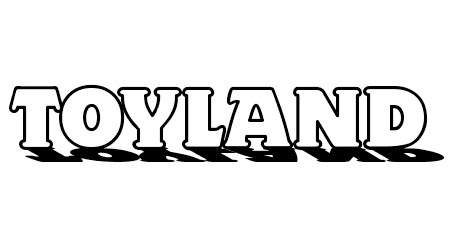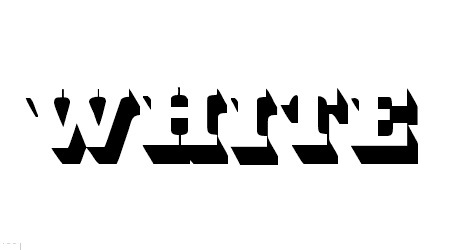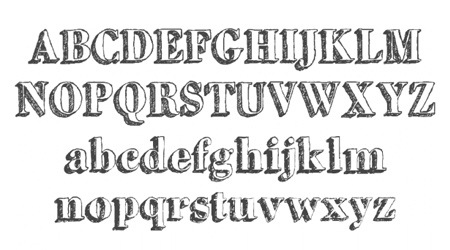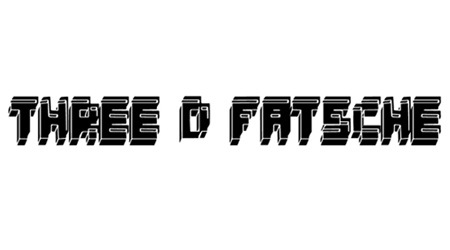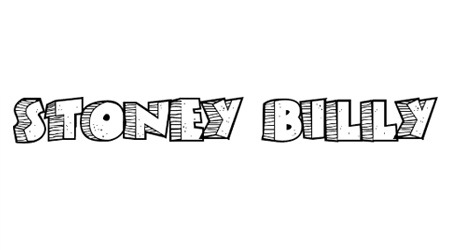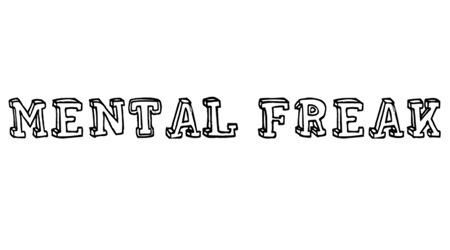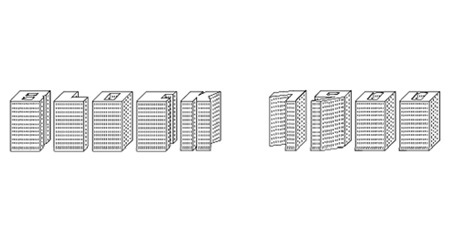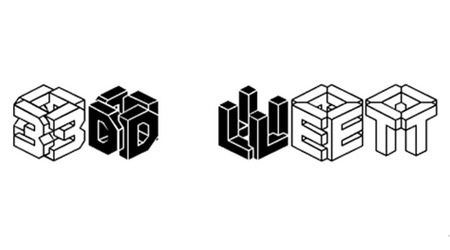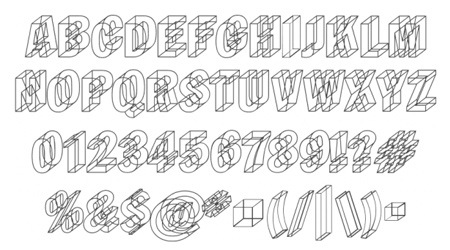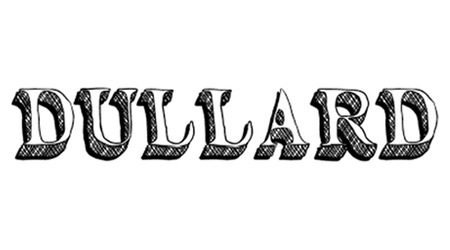
25 бесплатных 3D шрифтов
3d-шрифты В этой подборке, вам будут продемонстрированы шрифты хорошо знакомые каждому. Это шрифты в стиле 3D. Такие шрифты очень часто используют а дизайне постеров. Они способны добавить глубины изображению и придать стильный эффект дизайну в целом.
Тут вы найдете 25 различных 3D шрифтов. Все их вы сможете загрузить абсолютно бесплатно. Загружайте 3D шрифты и делайте свои работы более привлекательными!
Шрифт DULLARD
Шрифт
Наведенный шрифт esquisito
Наведенный шрифт
Кубический шрифт cubus
Кубический шрифт
Забавный шрифт shutdown!
Забавный шрифт
Округлый шрифт Chocolate Drops
Округлый шрифт
Шрифт с пикселями Blockstepped
Шрифт с пикселями
Размытый шрифт Snarky’s Machine
Размытый шрифт
Шрифт в восточном стиле Hawkeye
Шрифт в восточном стиле
Объемный шрифт Xtrusion
Объемный шрифт
Шрифт с тенью TOYLAND
Шрифт с тенью
Крупный шрифт White
Крупный шрифт
Шрифт в стиле гранж GrutchShaded
Шрифт в стиле гранж
Стильный шрифт 3d-fatsche
Стильный шрифт
Иллюстрированный шрифт Stoney Billy
Иллюстрированный шрифт
Тонкий шрифт Mental Freak
Тонкий шрифт
Шрифт в виде блоков block 1900
Шрифт в виде блоков
Затертый шрифт 3d noise
Затертый шрифт
Шрифт в виде кубов 3d-let
Шрифт в виде кубов
Шрифт с отражением Wireframe
Шрифт с отражением
Жирный крупный шрифт jabjai
Жирный крупный шрифт
Аккуратный шрифт Post Office
Аккуратный шрифт
Шрифт Hillock
Шрифт 3D
Шрифт с тенями Comic Zine
Шрифт с тенями
Креативный шрифт maze
Креативный шрифт
Высокий шрифт blog the impaler
Высокий шрифт